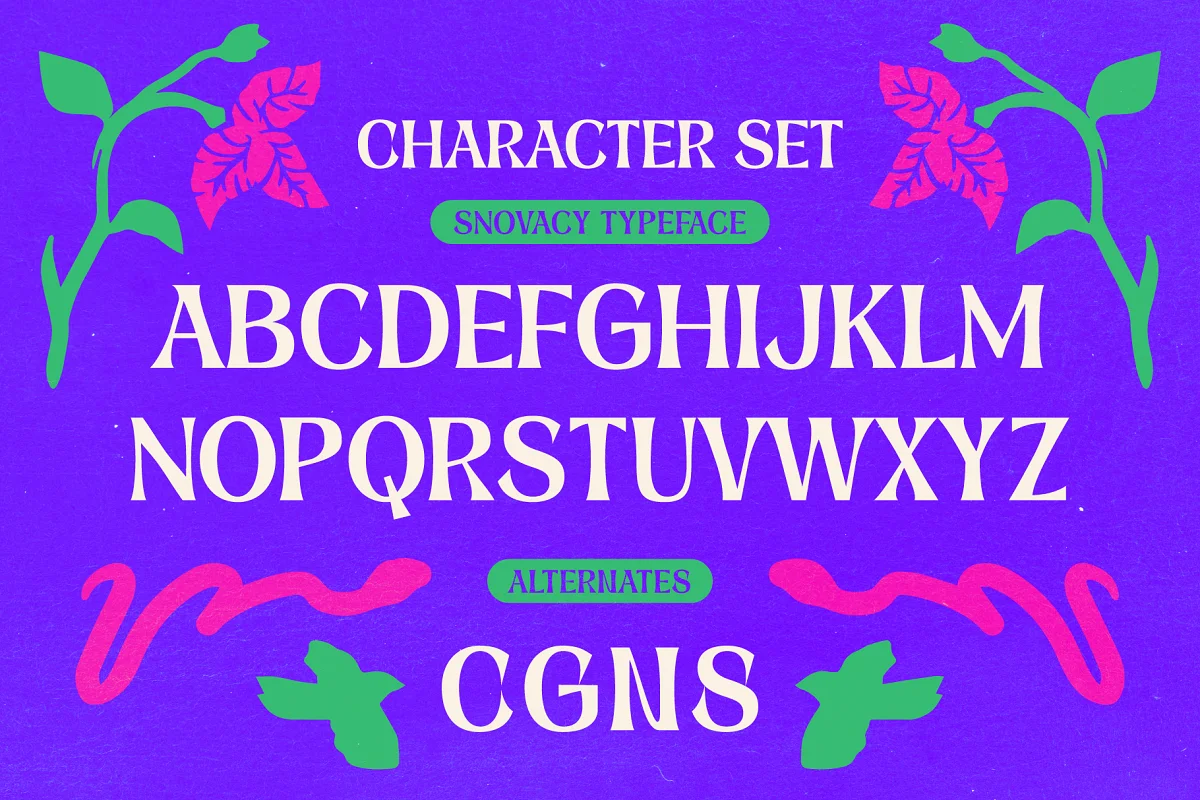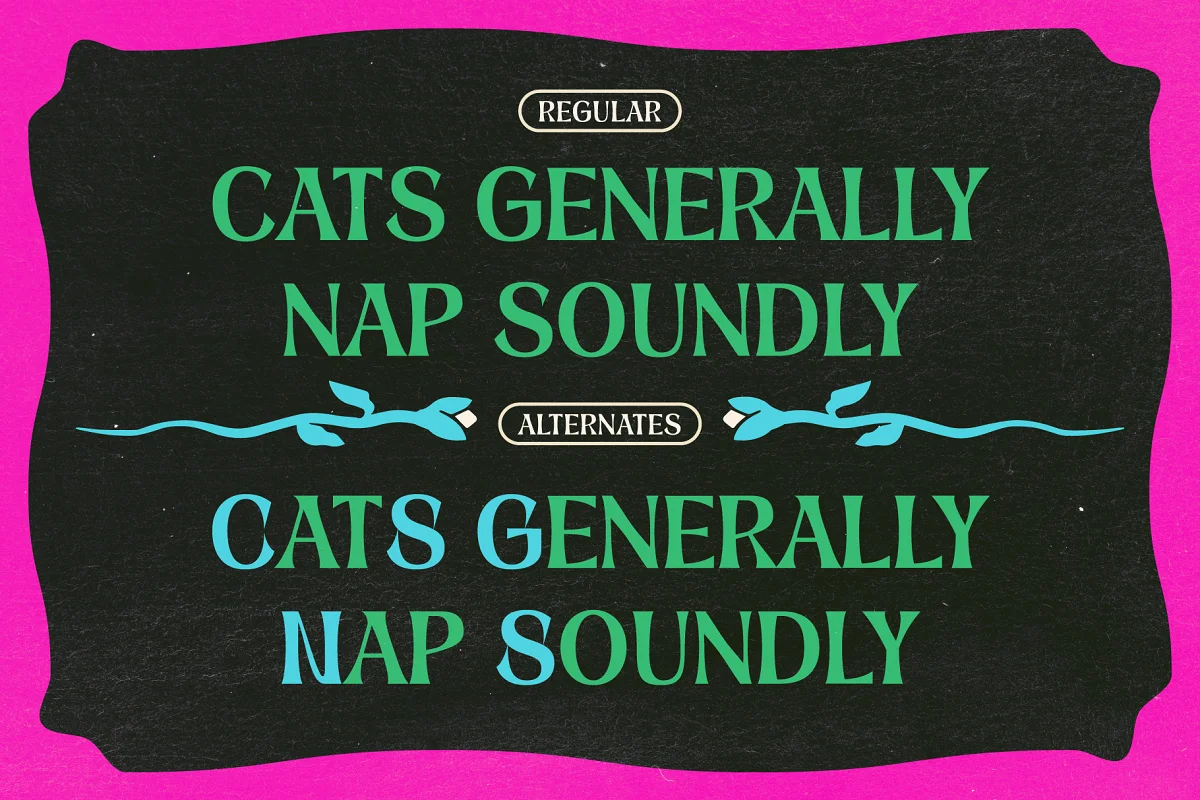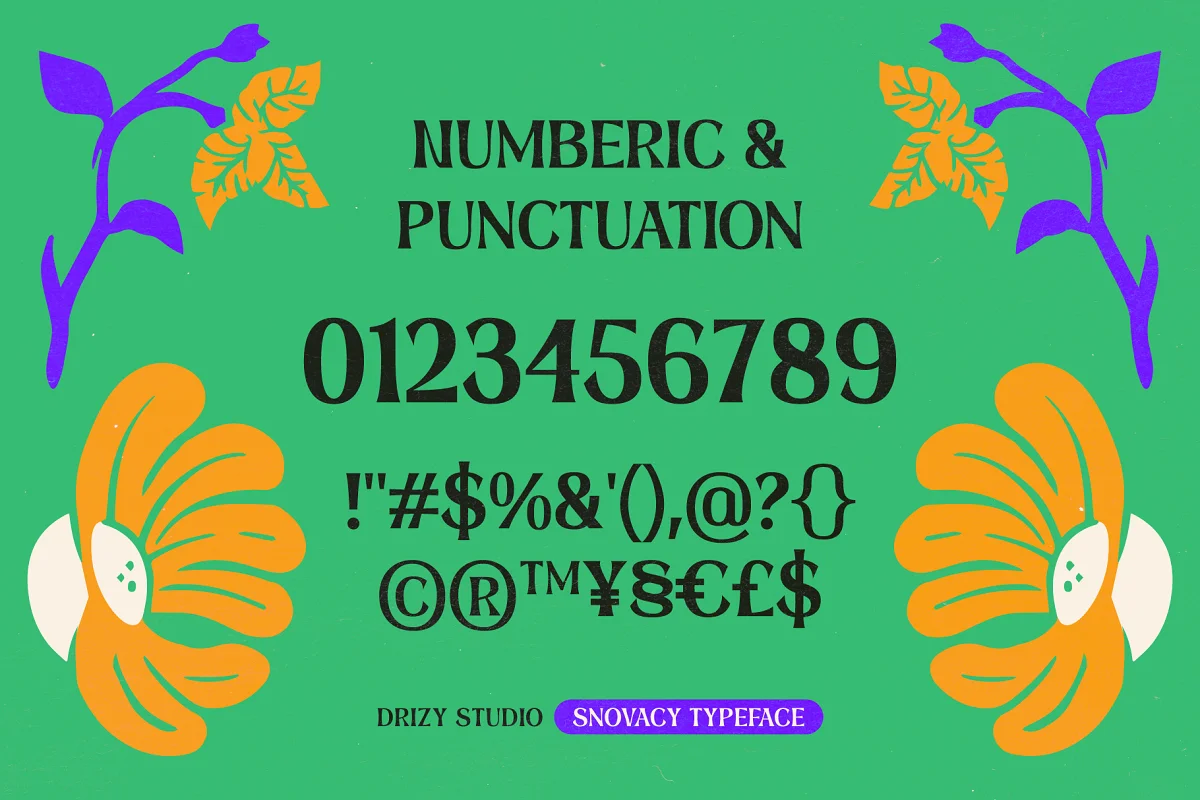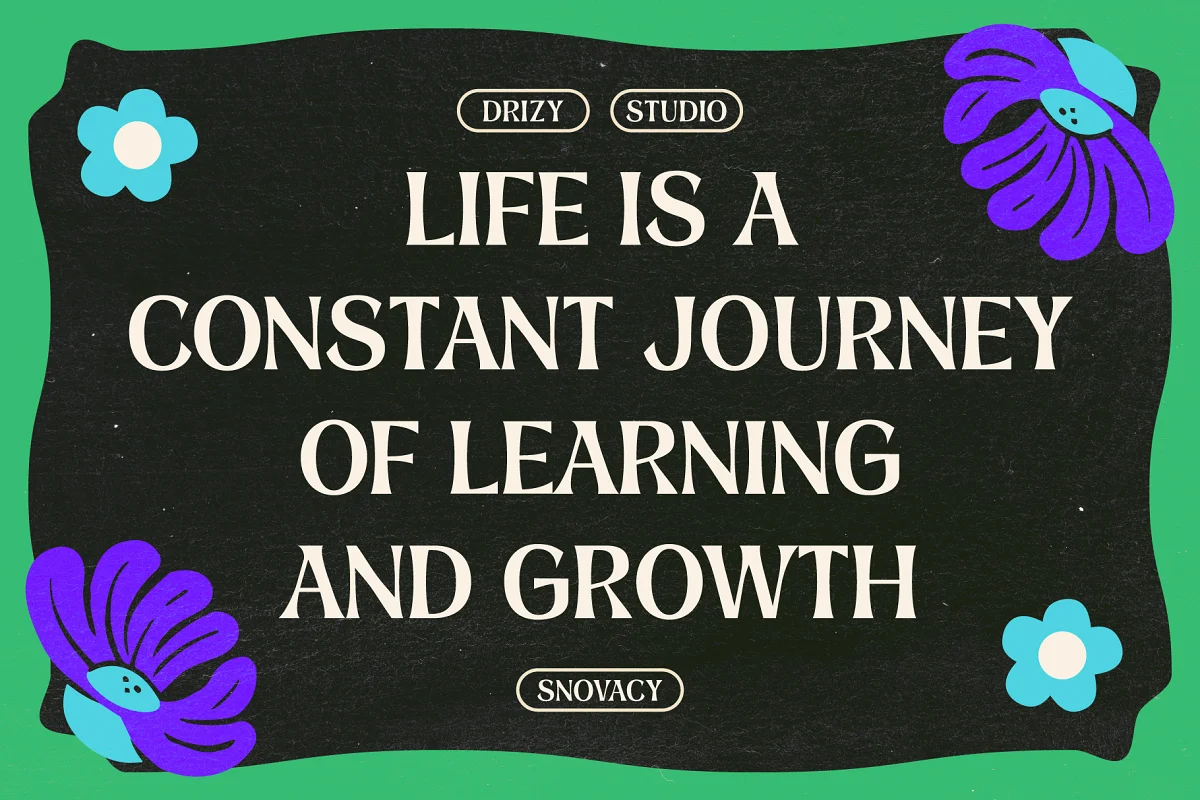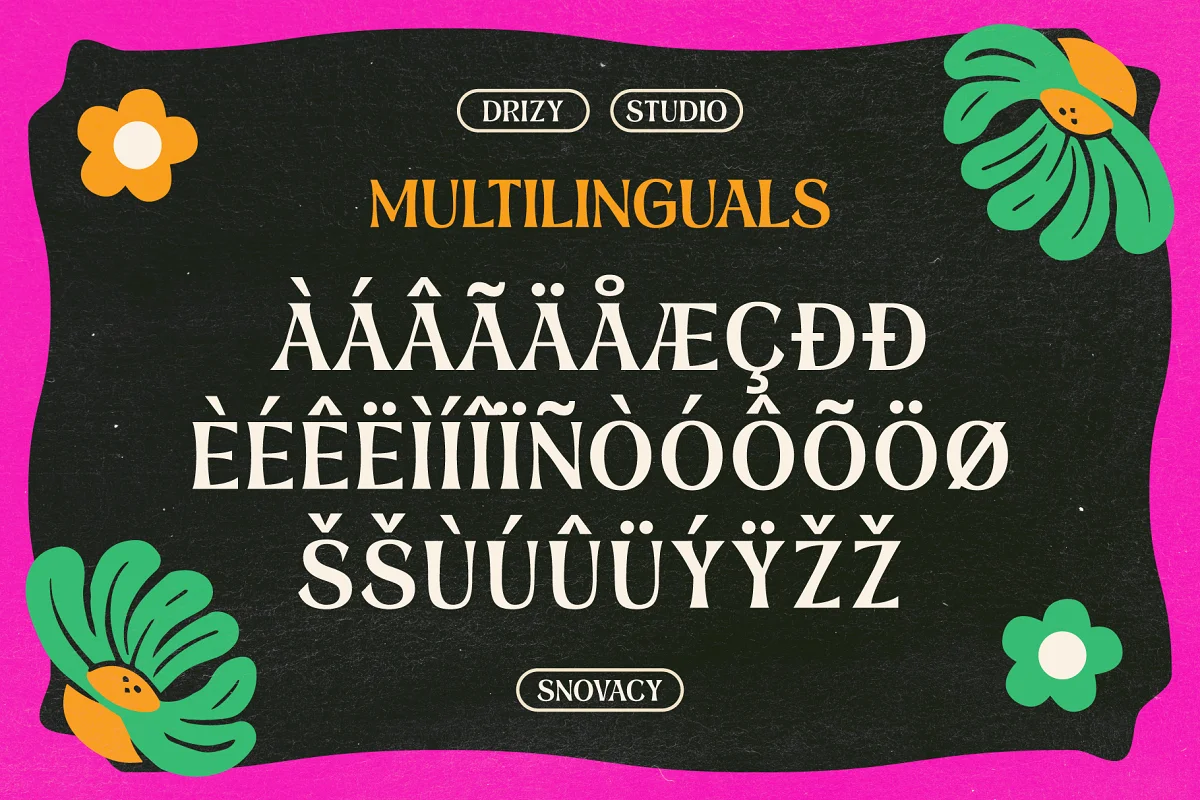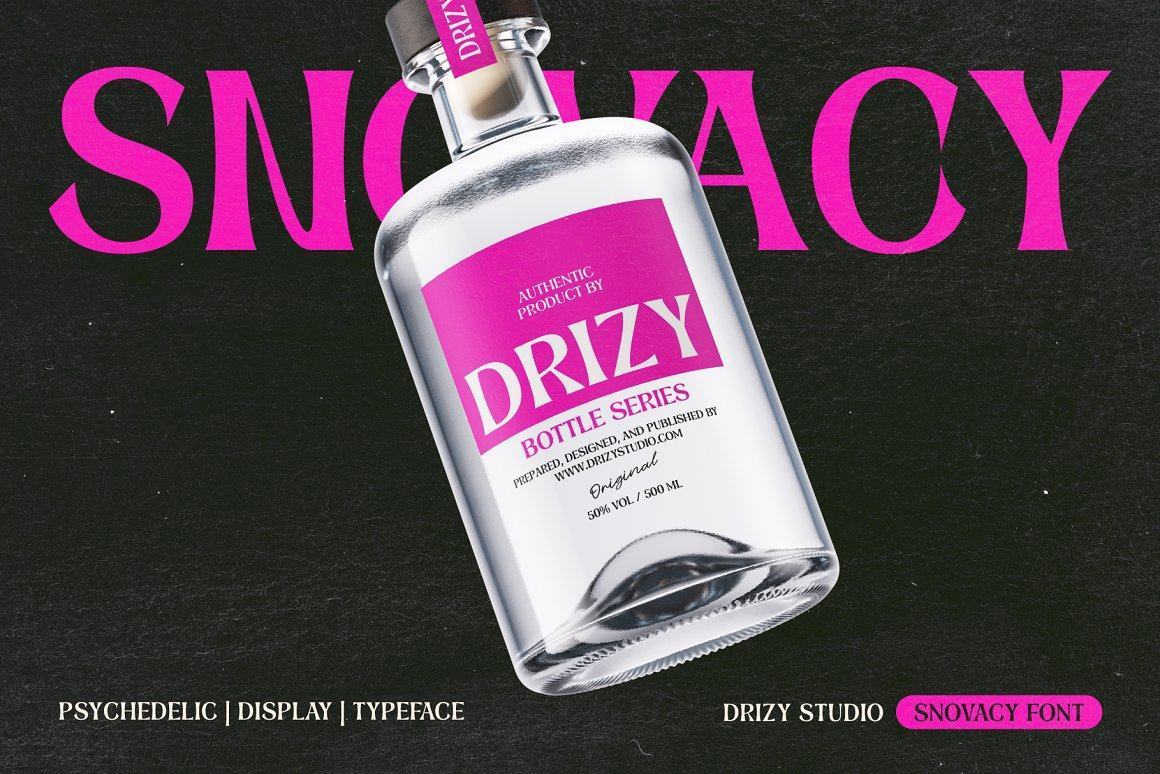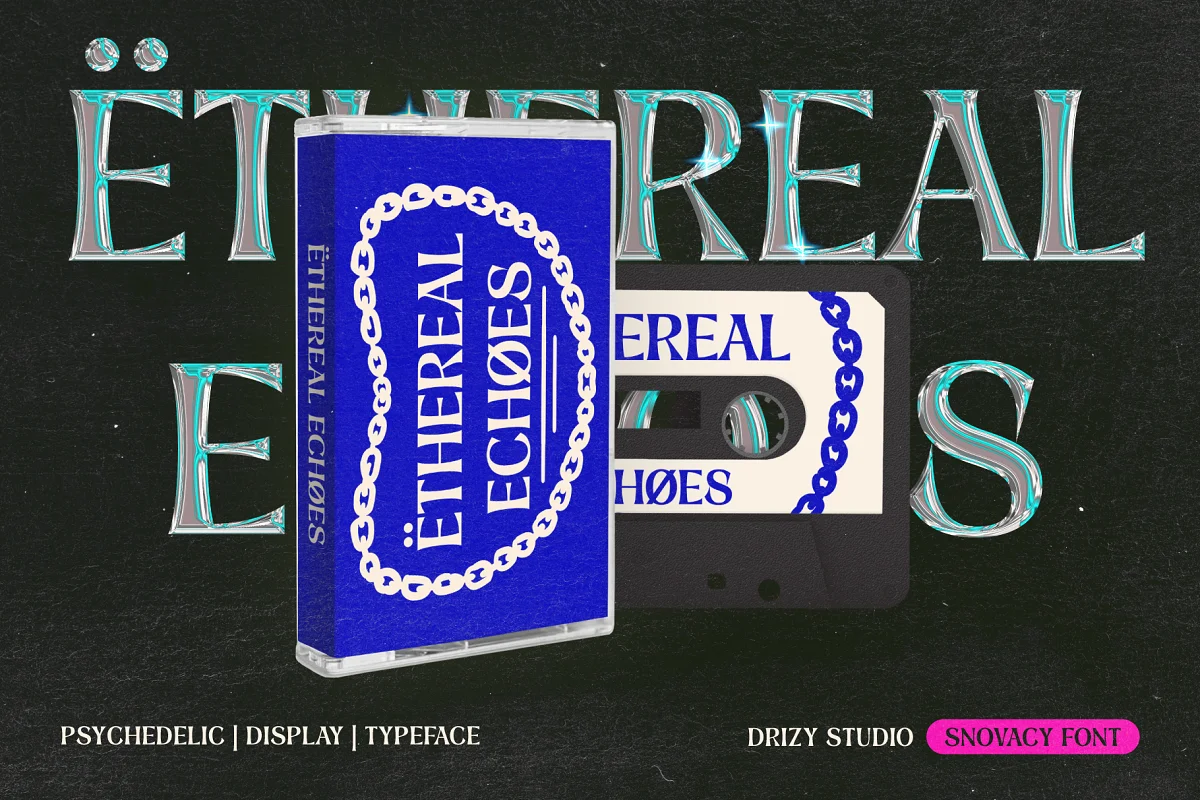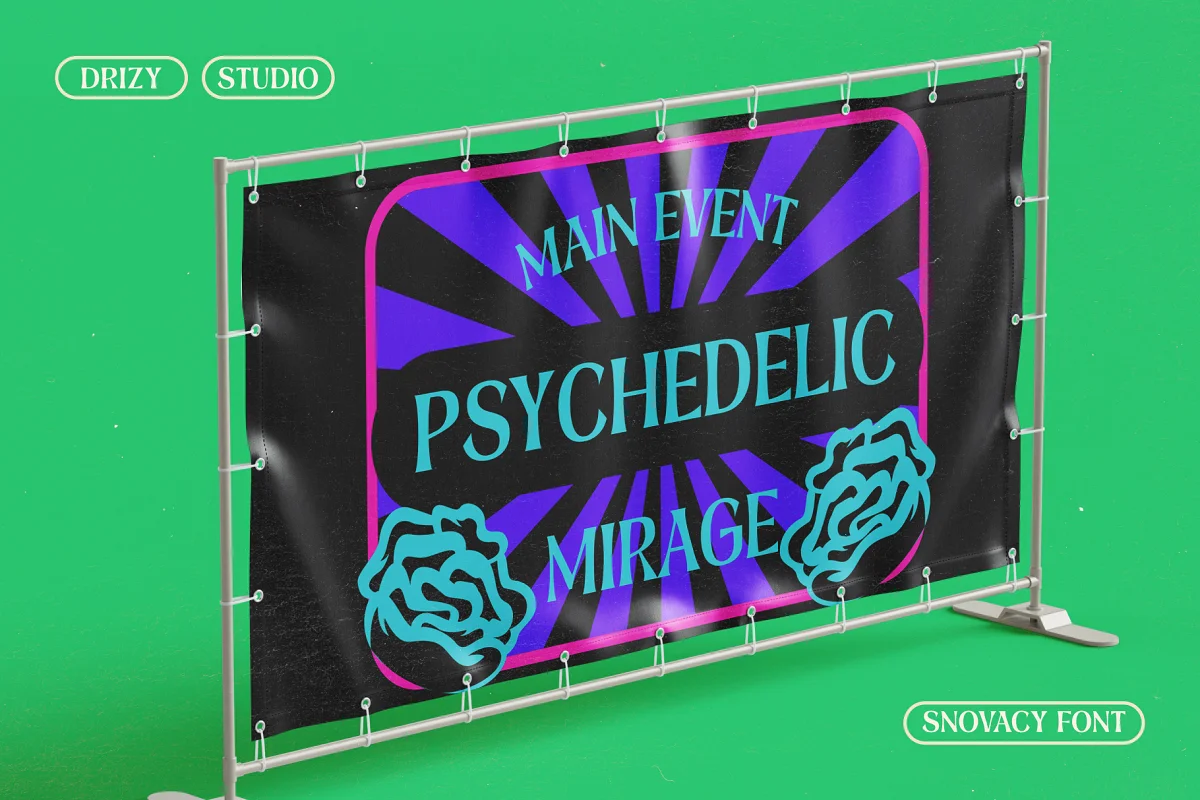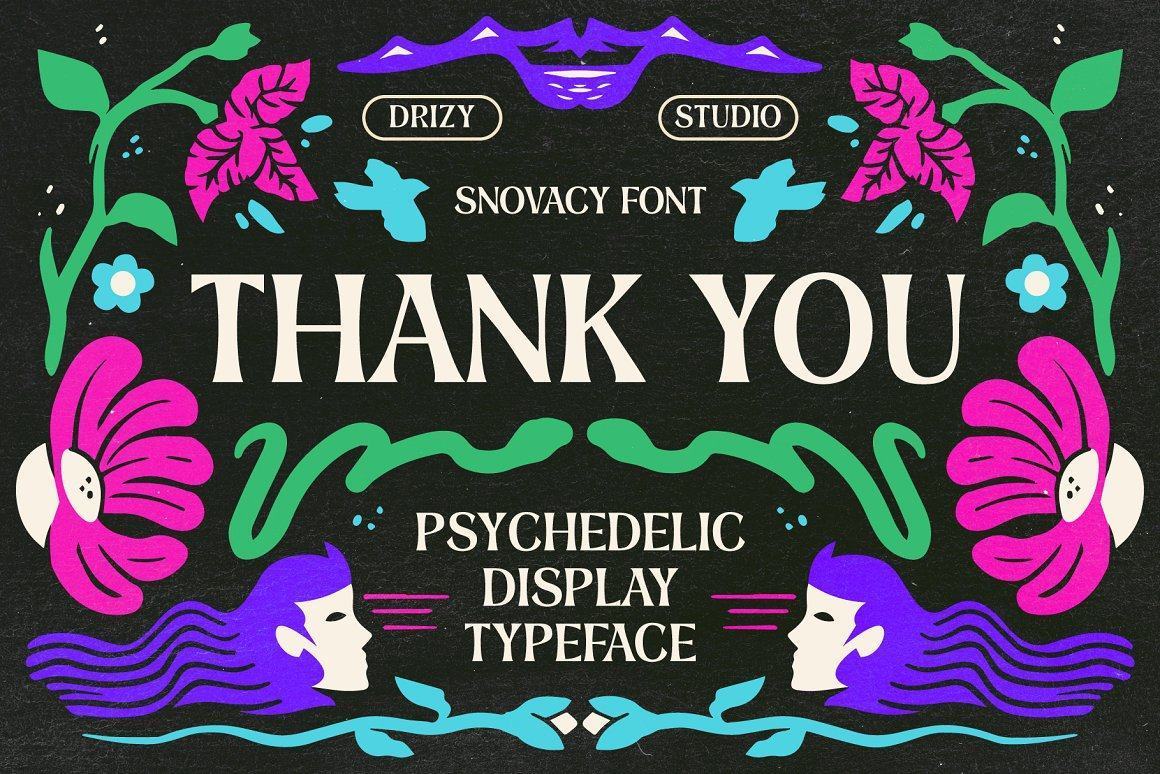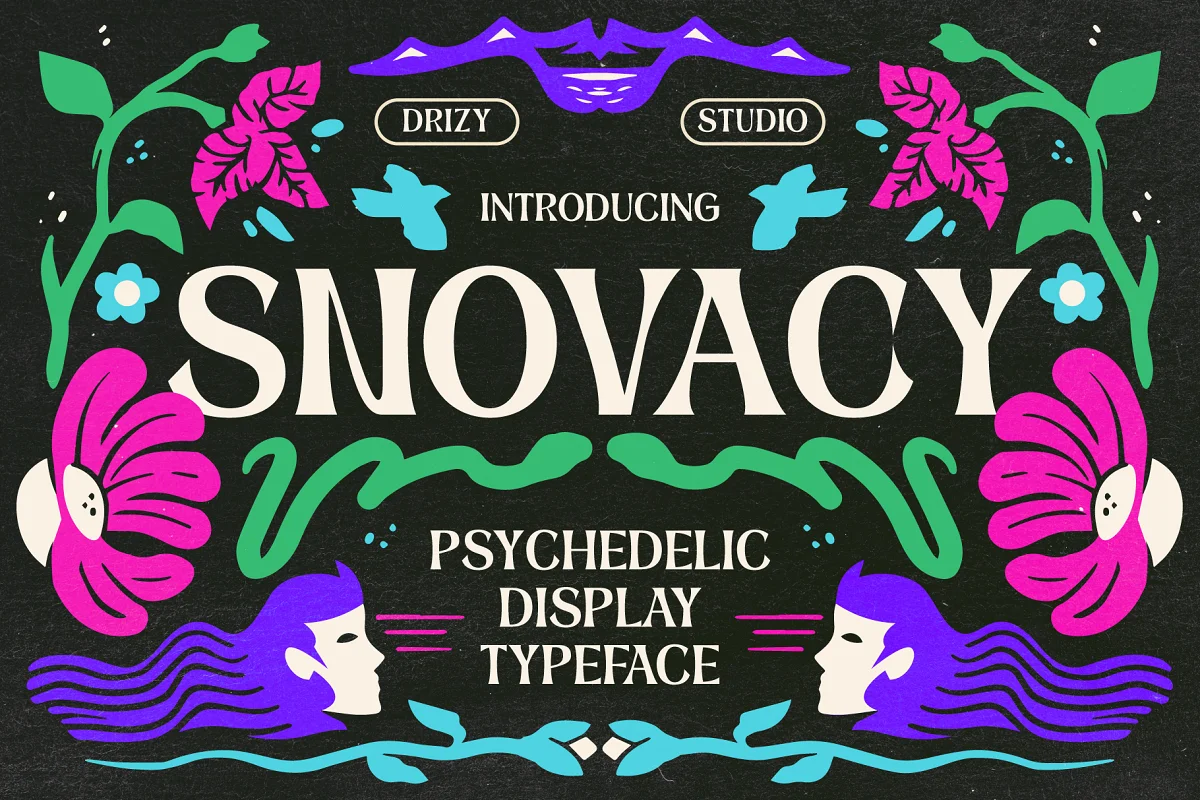
Snovacy – Phông chữ hiển thị ảo giác
Giới thiệu Snovacy, một phông chữ hiển thị Hoa ảo giác thẩm mỹ đầy mê hoặc và sống động, mang đến sự bùng nổ sáng tạo cho các dự án của bạn. Với sự pha trộn độc đáo giữa những đường cong kỳ lạ, đường nét táo bạo và các chi tiết phức tạp, Snovacy nắm bắt được bản chất của kỷ nguyên ảo giác, thêm nét quyến rũ cổ điển vào thiết kế của bạn.